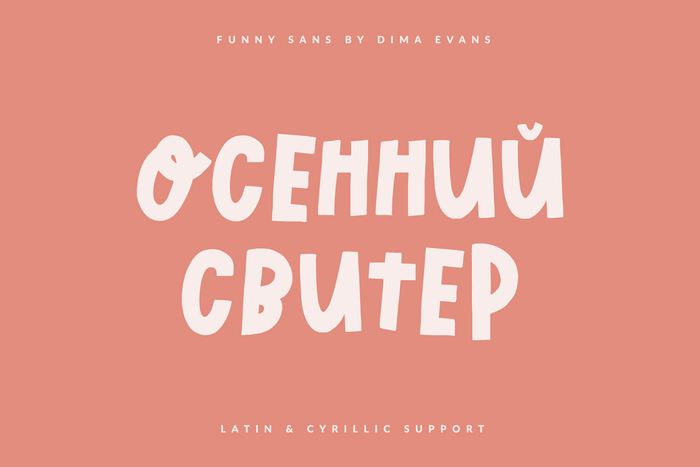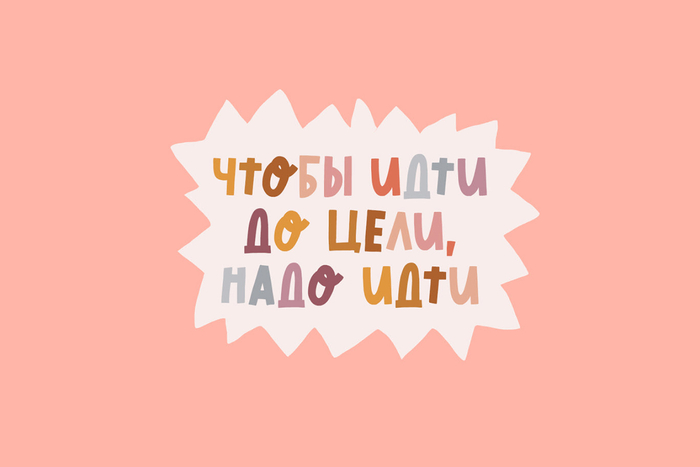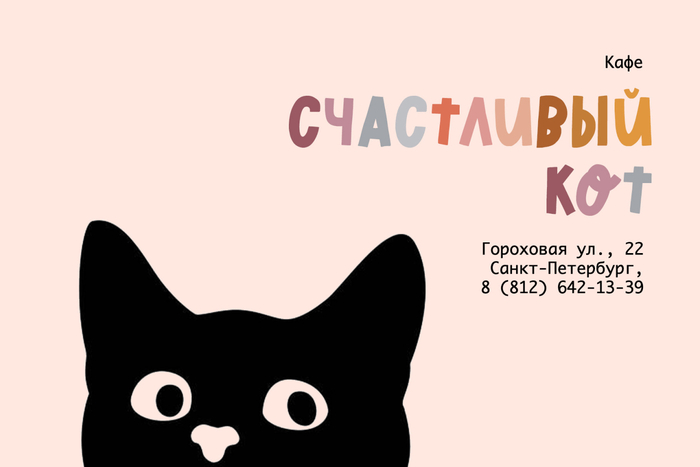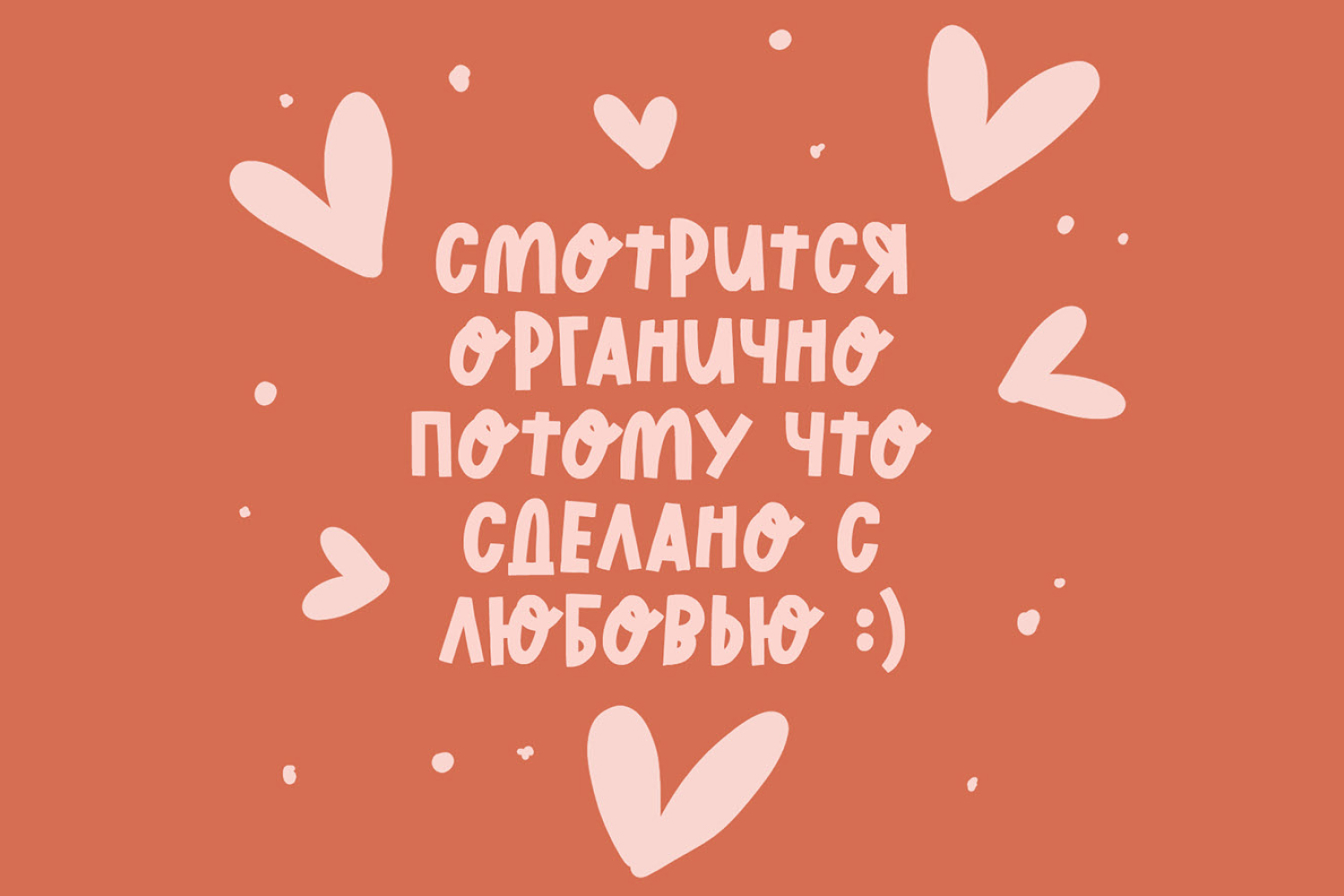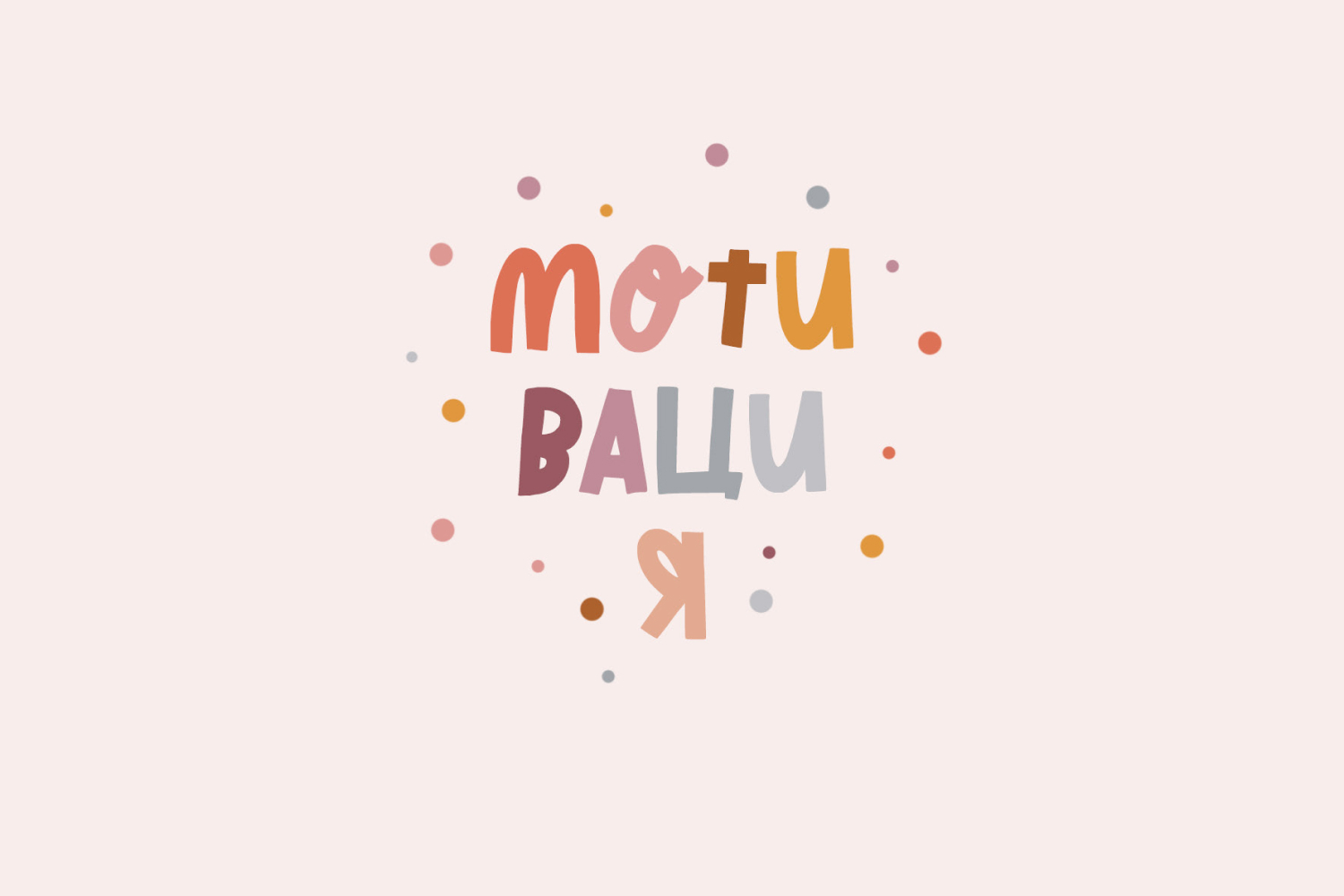
Шрифт "Осенний свитер"
Осень. Суббота. А значит поделимся чем-то архивным. Пора одеть на себя осенний свитер, съесть мягких французских булочек и выпить теплый чай.
Автор: Sup Fonts.
ps. Хороним букву "Т" ?)